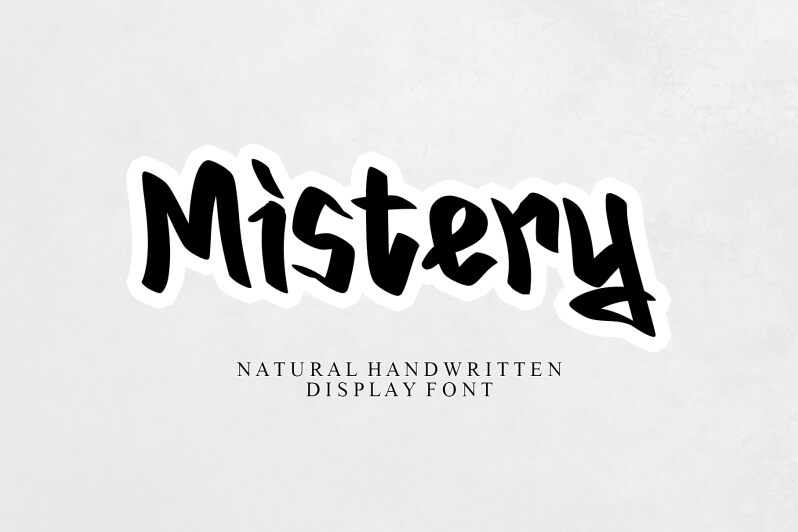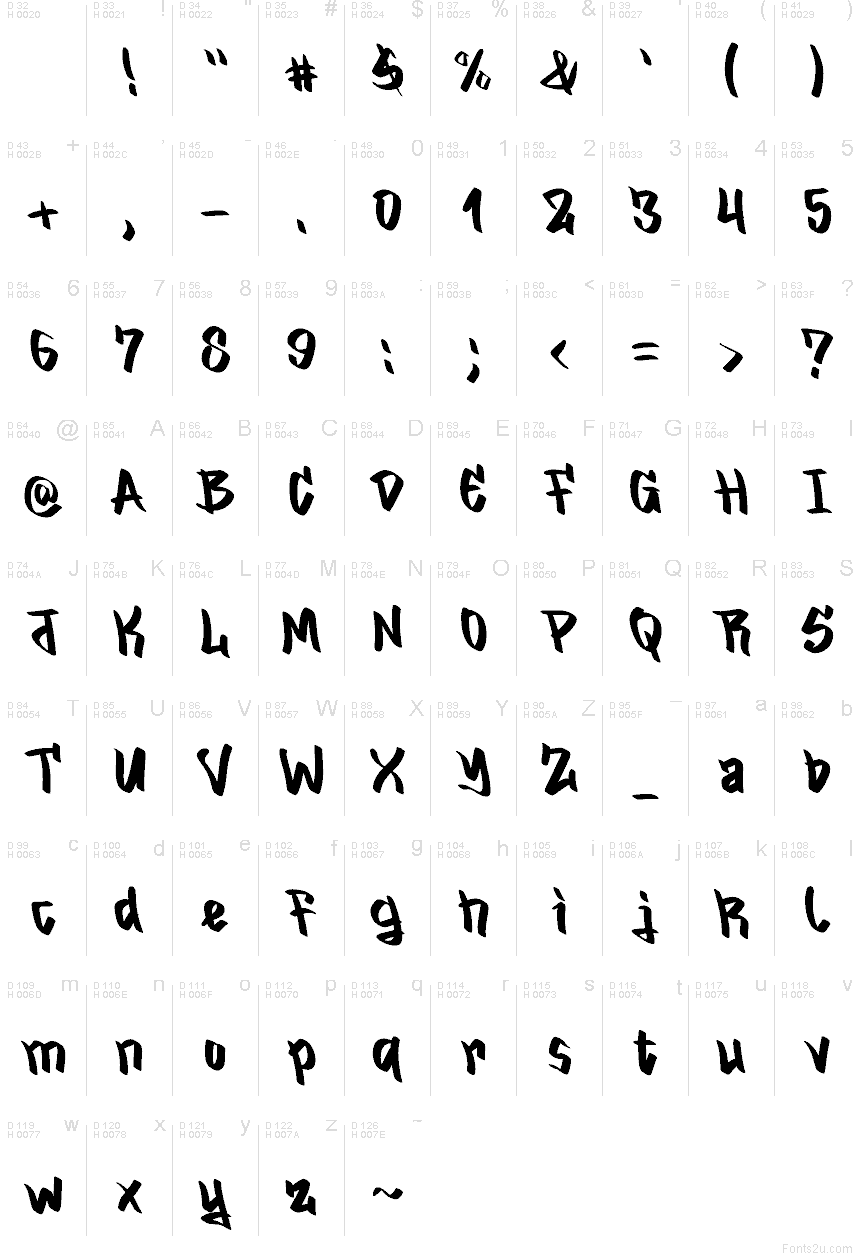
Mistery, které v roce 2021 vytvořil Letterafa, je bezplatné písmo typu graffiti script s vysokými, nezkrotnými literami a prudkými změnami tloušťky tahu. Špičaté spoje a háčkovitá zakončení dodávají tvarům neklidný ráz. Nestejná výška znaků vnáší do každého řádku dojem ručně kreslené improvizace.
V kombinaci s pouliční fotografií nebo drsnou komiksovou grafikou může nápis přirozeně splynout s obrazem na hudebních plakátech, skate oblečení i promo materiálech ke hrám. Jeho syrový, rošťácký charakter se obzvlášť hodí pro akce pro mládež a nezávislé zábavní značky.